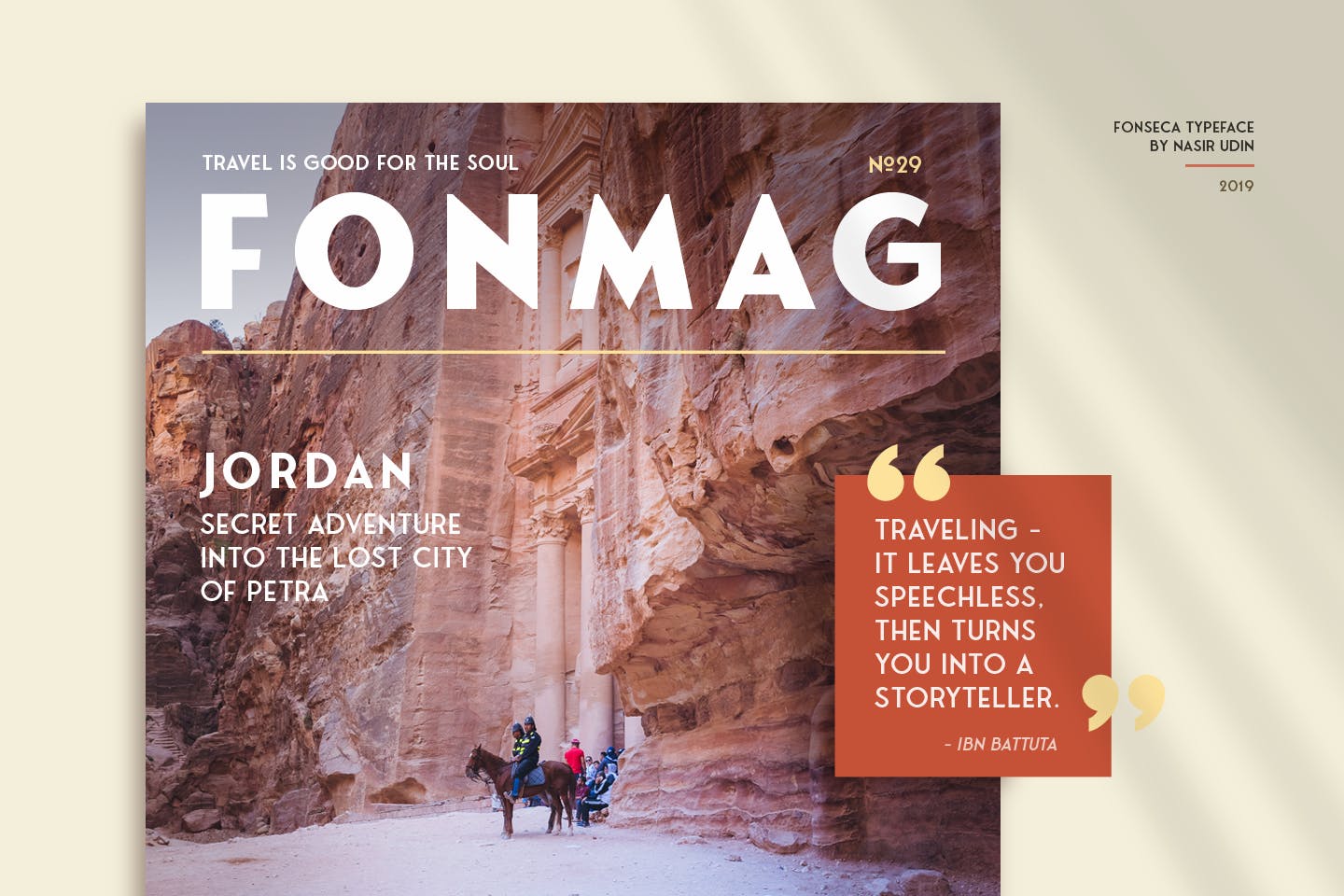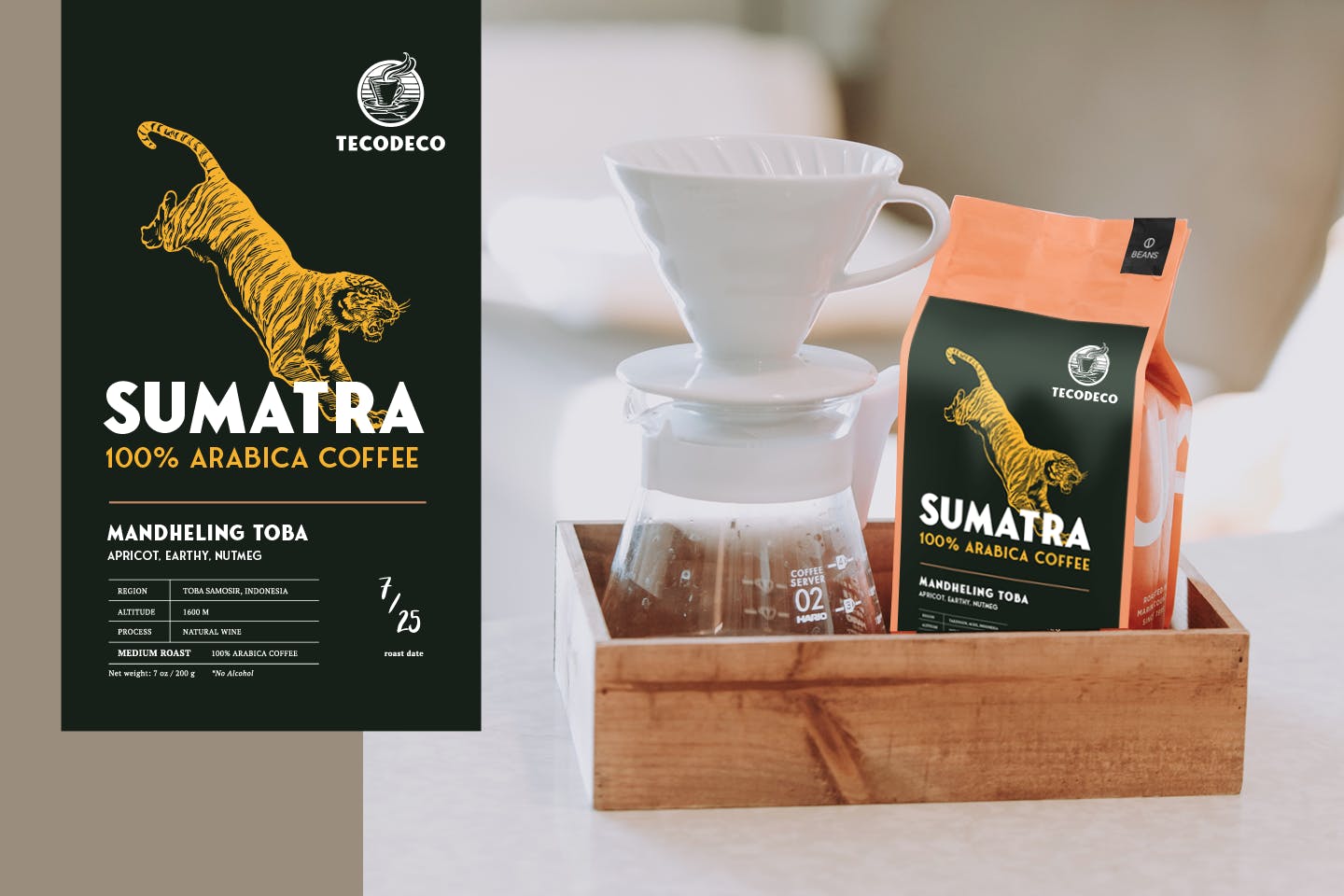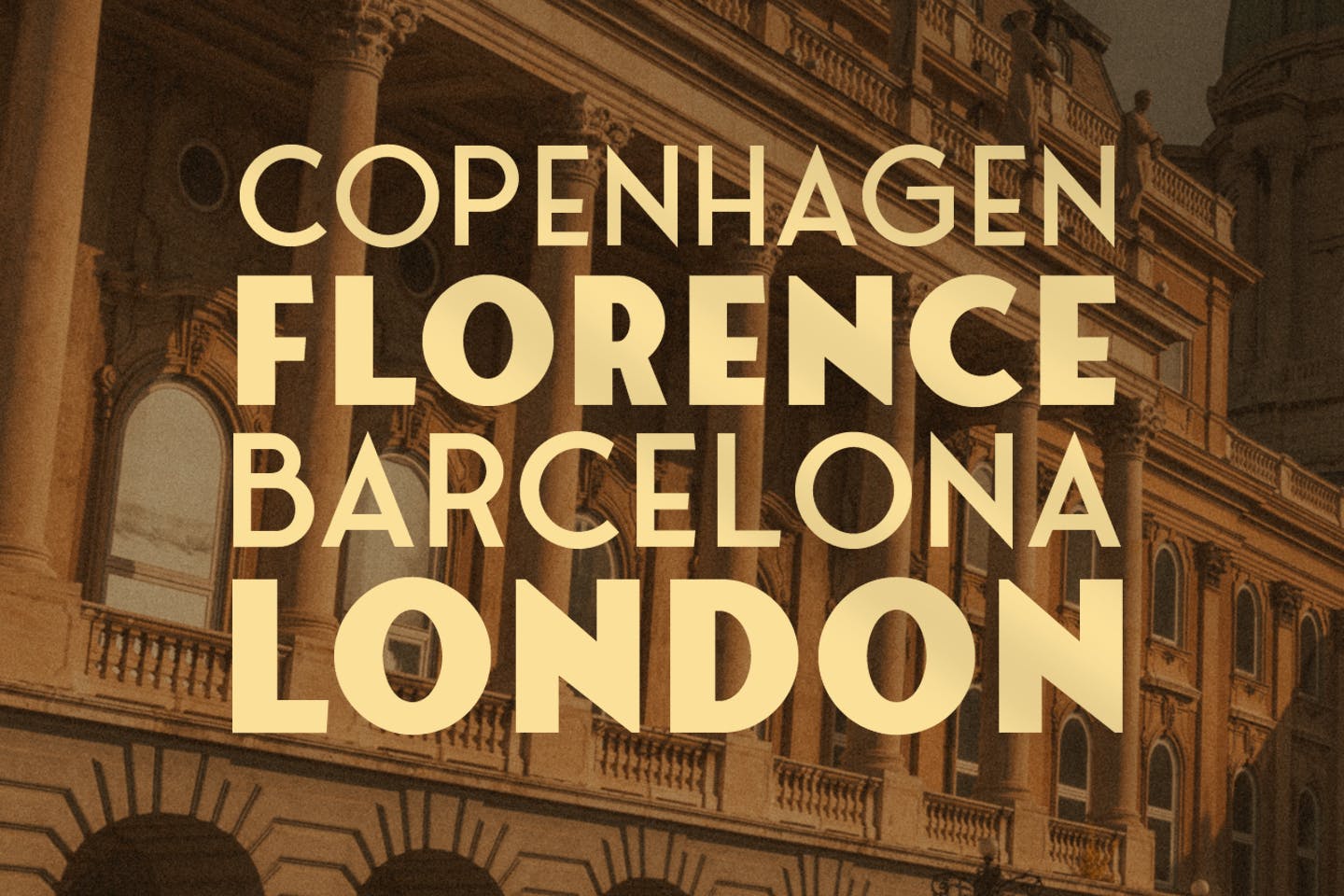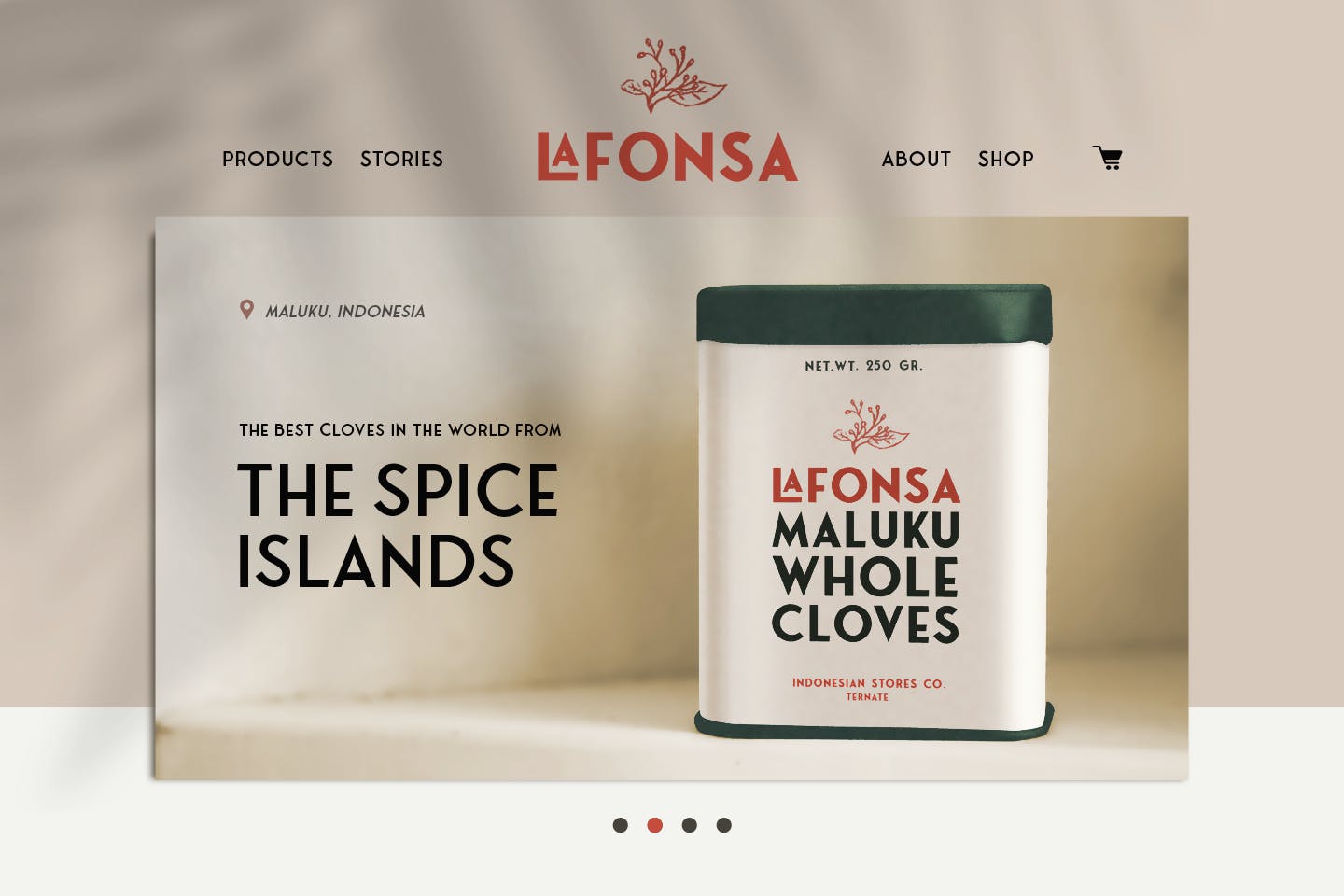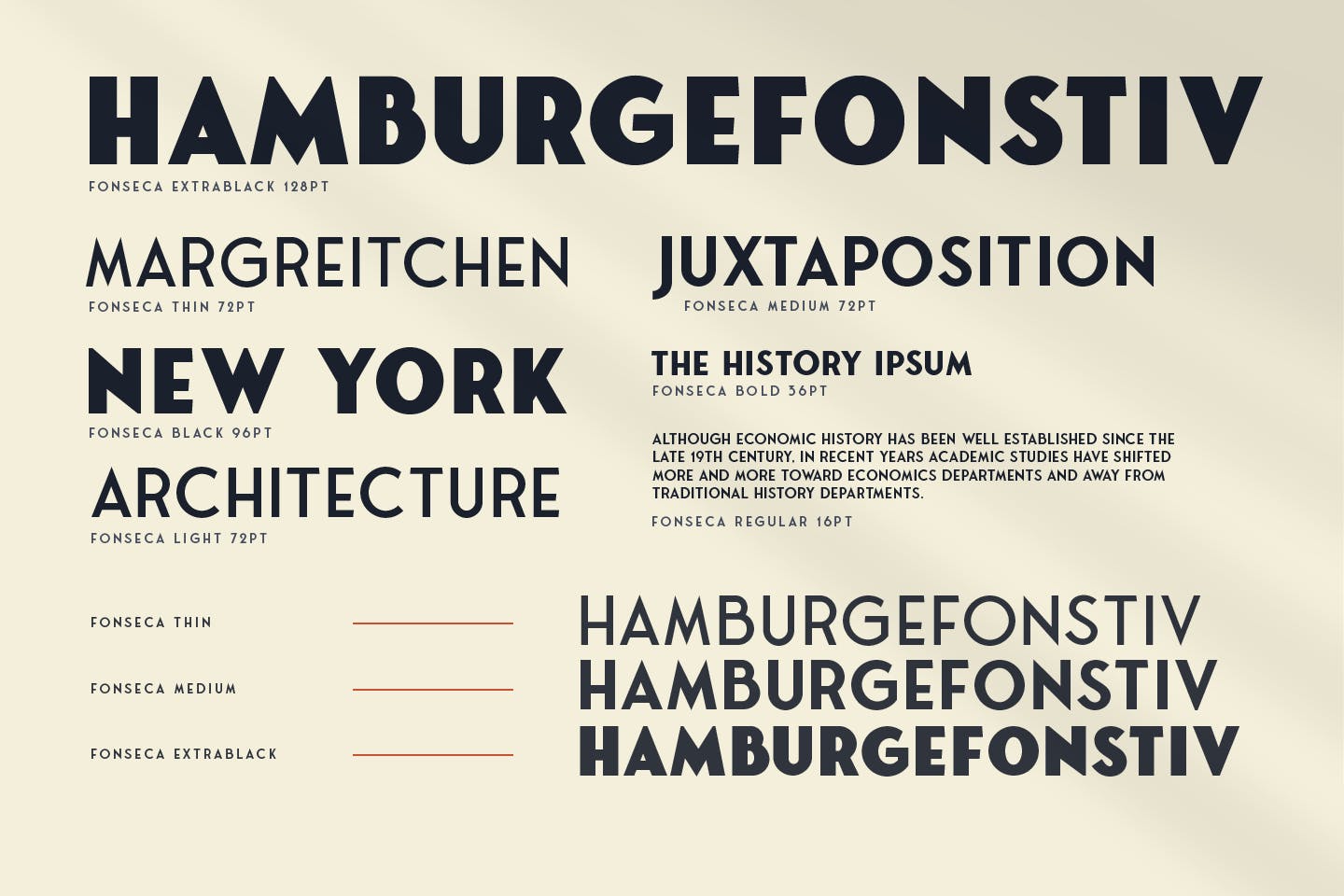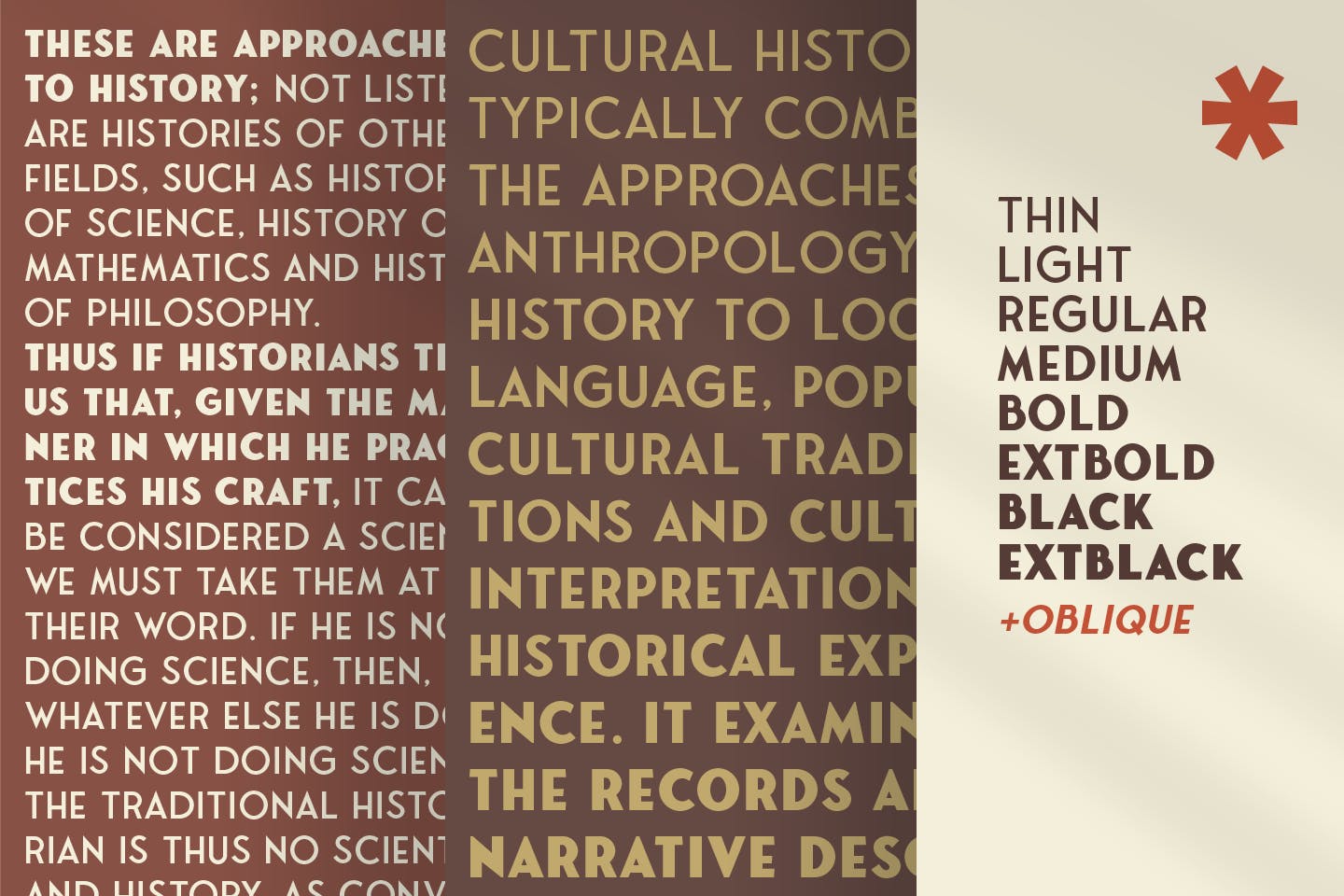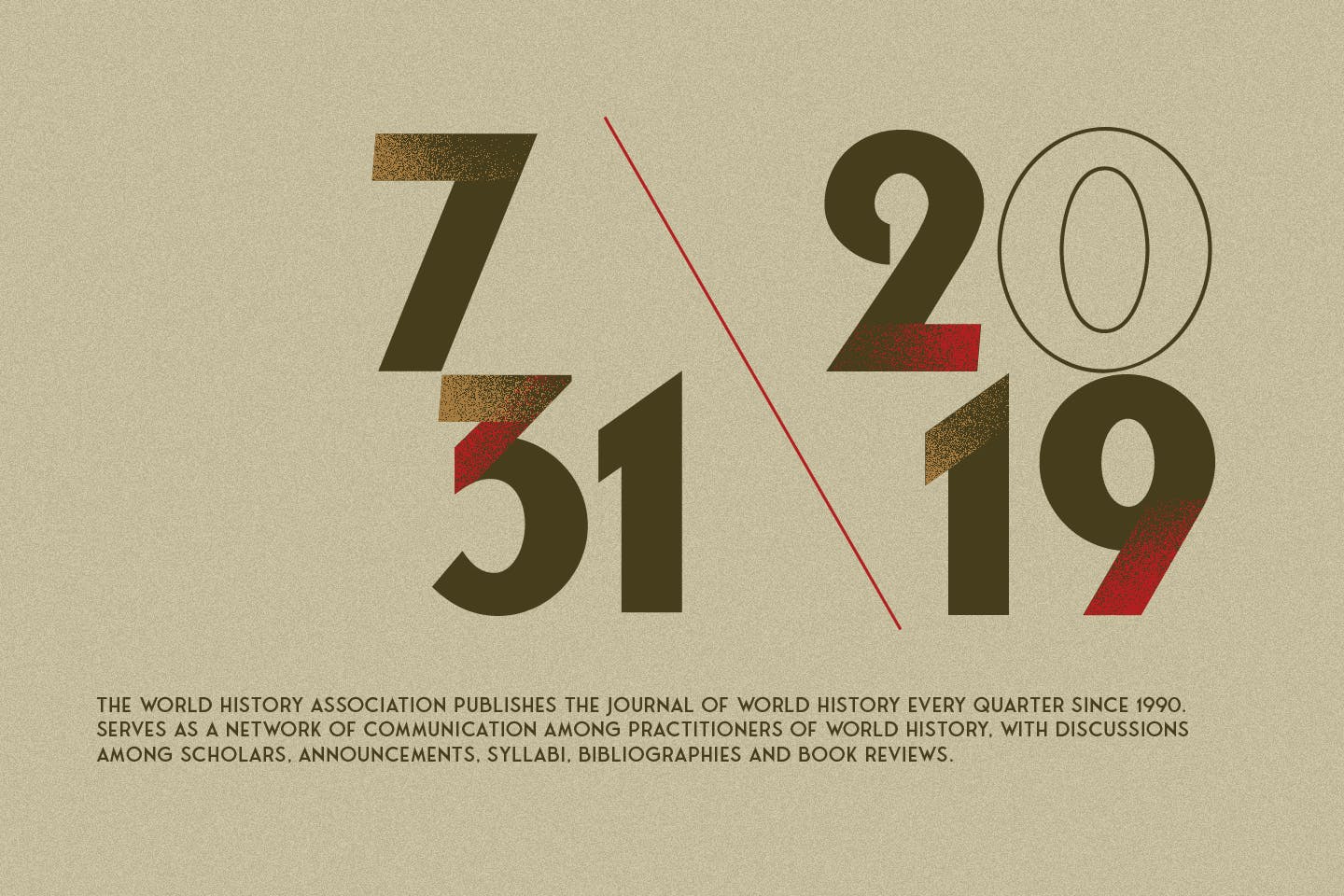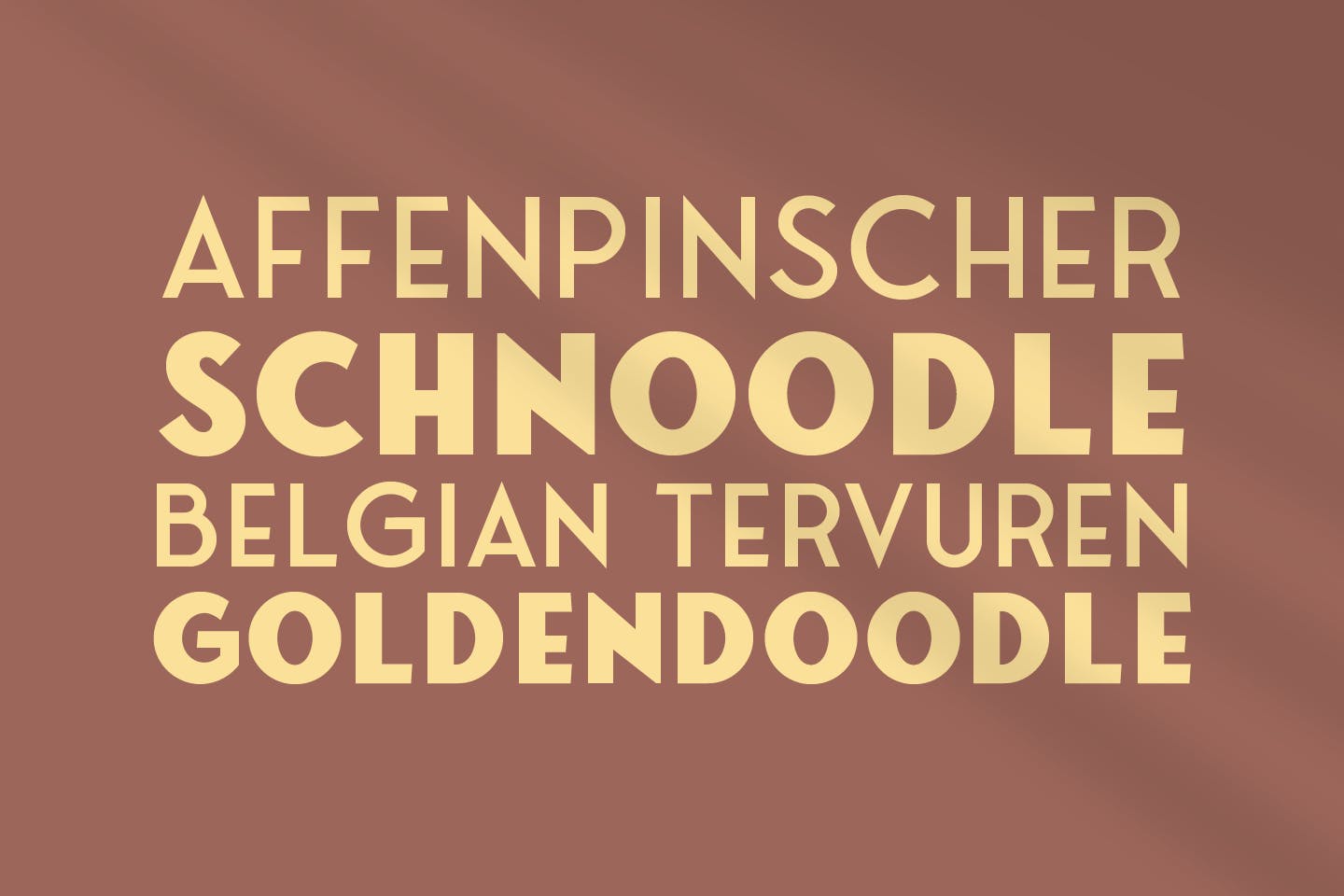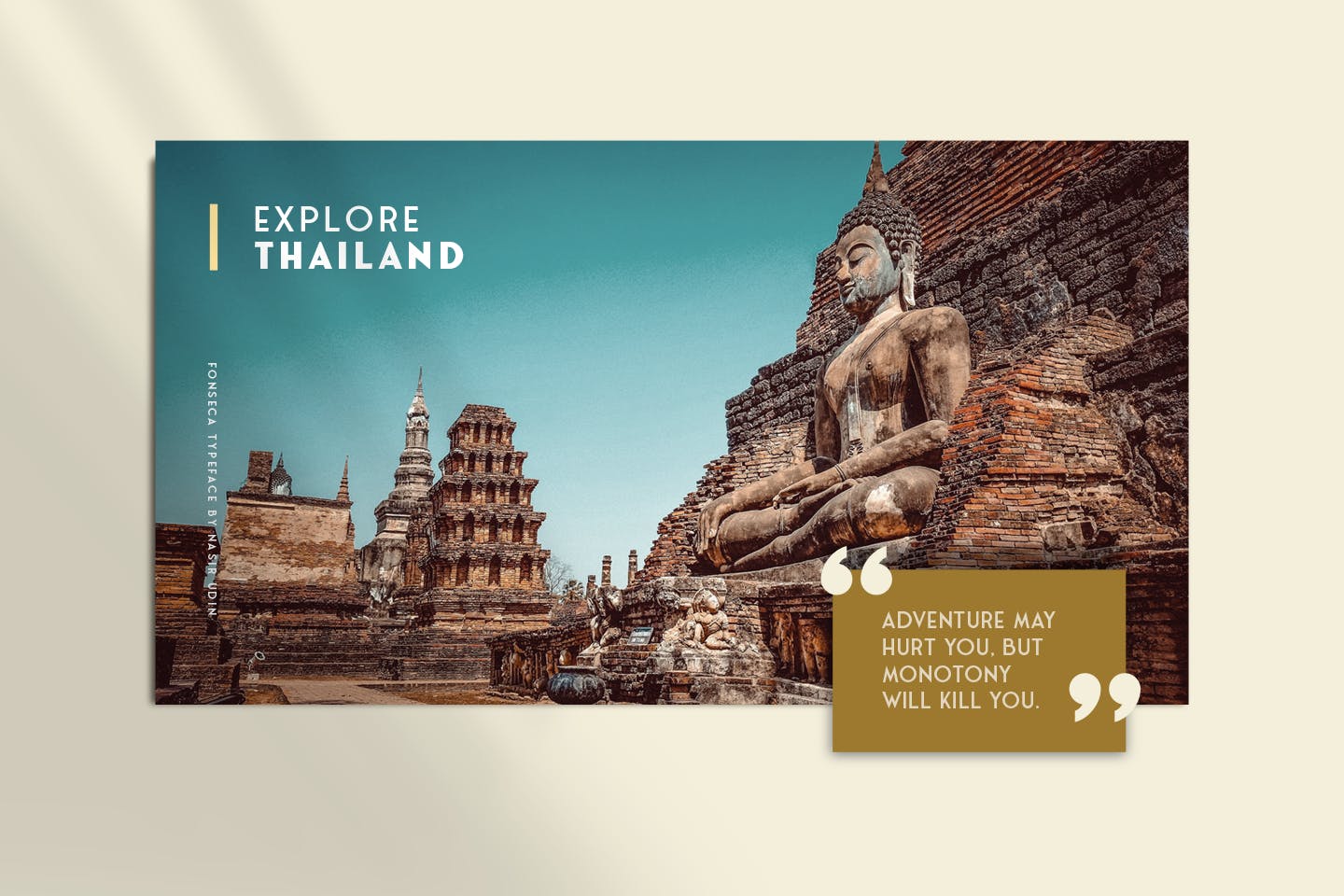
فونت فونسکا یک فونت مدرن بدون سریف است که الهامگرفته از طراحی آرت دکو و پوسترهای تایپوگرافی اوایل قرن بیستم میباشد. کلید این خانواده تمامحروف، فرمهای هندسی ساده و مدرن است.
ظاهر مدرن و بازسازیشده این فونت، آن را برای ارائه هر محتوایی مربوط به سفر، تاریخ و فرهنگ به شیوهای مدرن مناسب میسازد. این خانواده نمایشی برای تیترها، پوسترها، لوگوها، پروژههای برندینگ، مجلات و بستهبندیها ایدهآل است.
- جایگزینهای استایلی برای حروف ‘O’ و ‘E’
- لیگچرهای خاص: LA LE LI LO LU